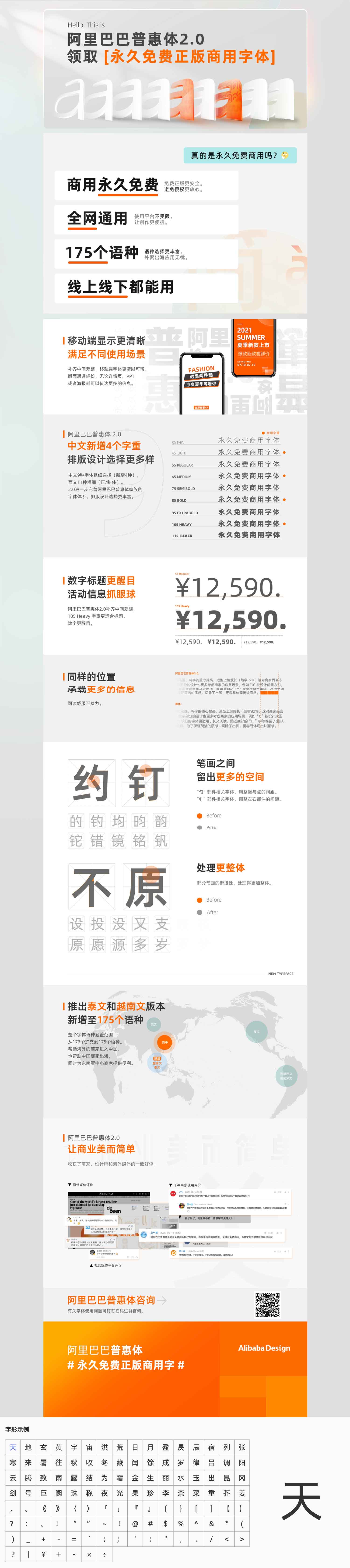
阿里巴巴普惠体 2.0
《阿里巴巴普惠体》是一款由中国企业首次发布的可面向全场景使用的免费商用正文字体。可永久免费正版商用的阿里巴巴普惠体,中文字体多采用现代简洁的笔画,造型上偏瘦长,并将字的重心提高。字体笔画上也做了一些简化,如较粗的标题字省略出脚部分,更显简洁。
在原有的1.0版本基础上,《阿里巴巴普惠体2.0》的中文字体优化了部分字体结构、新增4个字重(字体粗细),从5个增为9个字重。字库共囊括222,841个字符,覆盖全球175个语种。